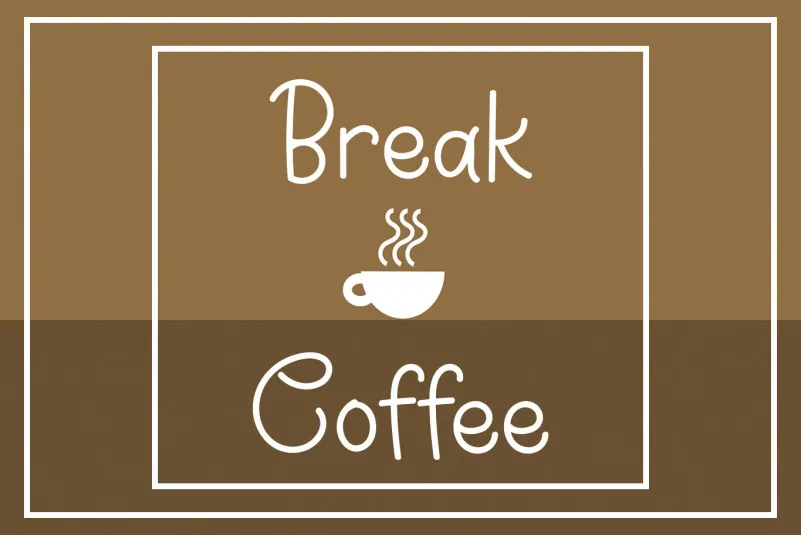
Break Coffee Font – Download Grátis
Esta é uma fonte escrita à mão, elegante e delicada. Ela tem um clima limpo e suave, com traços finos perfeitos para qualquer design que você queira adicioná-la ao seu trabalho. Seu charme suave e alegre encaixa-se perfeitamente em designs de café ou outros ambientes relaxantes. A fonte é uma escolha ideal para aqueles que buscam um toque personalizado e delicado, especialmente se estiverem buscando algo casual e acolhedor sem abrir mão da elegância. O designer Erik Studio criou esta fonte única, adequada tanto para gráficos digitais quanto impressos. Ela será uma ótima adição a qualquer projeto de design que você desejar dar um toque pessoal e suave, tornando seus projetos ainda mais únicos e encantadores. Composto principalmente por letras pequenas e frases simples, essa fonte é perfeita para uso em designs de café ou outros ambientes onde o toque casual e acolhedor são valorizados. Seja uma logo, um logotipo, uma embalagem ou até mesmo sua própria identidade visual pessoal, esta fonte será uma escolha impecável.